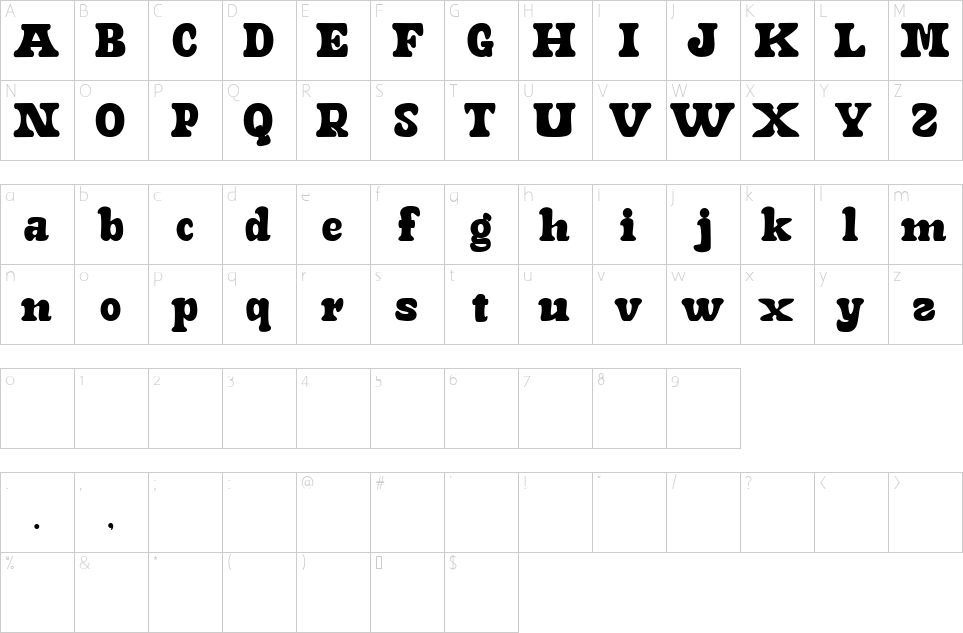
Augsburg Font – Fonte Grátis
Augsburg Font
Augsburg é uma fonte amigável e versátil que traz um ar de simplicidade e elegância à sua próxima projeto de design. Desenhada por Canden Meutuah, esta fonte pode ser facilmente adaptada para uso em sites, aplicativos, revistas e qualquer outro projeto que você esteja planejando. Com um design minimalista, a Augsburg combina perfeitamente com uma variedade de estilos, tornando-a uma opção versátil para designers gráficos. Se você está procurando uma fonte que seja both clássica e moderna, a Augsburg é uma ótima escolha para incorporar em seu design. Descarregada 1.170 vezes, a Augsburg é uma fonte que vale a pena explorar e experimentar. Seja para um projeto pessoal ou profissional, a Augsburg oferece uma maneira refinada e atraente de personalizar seu design.
Mapa de caracteres da fonte Augsburg Font